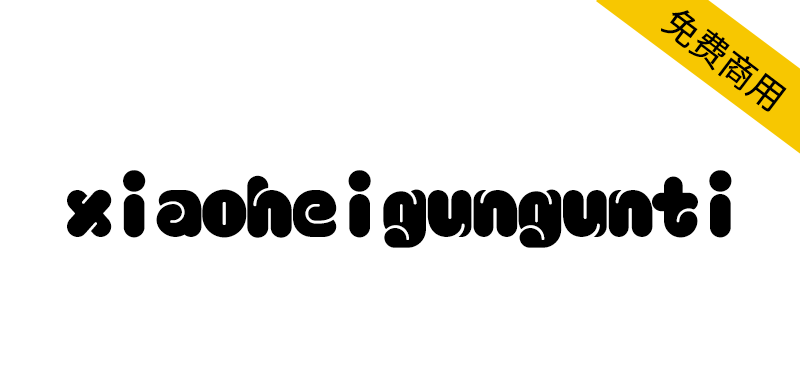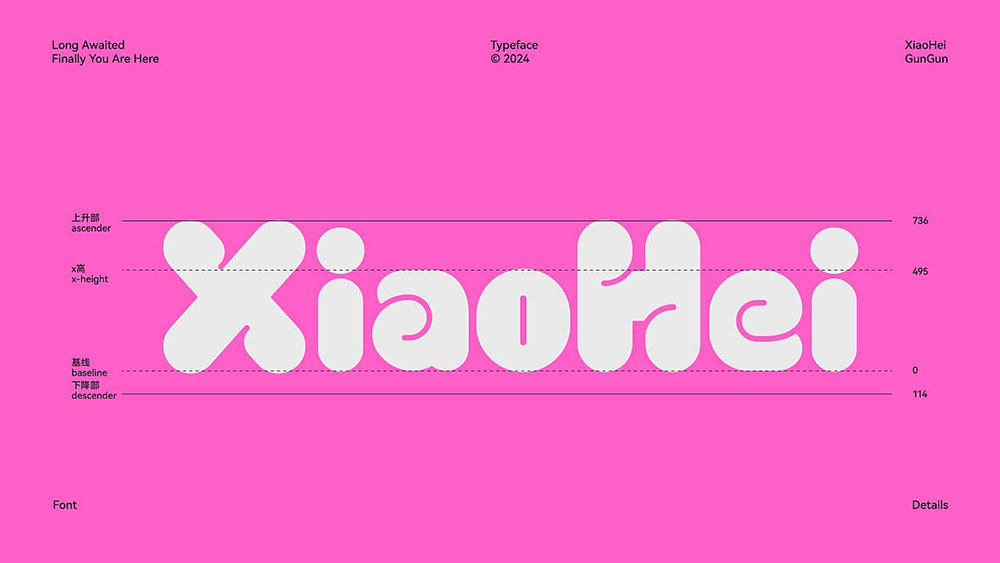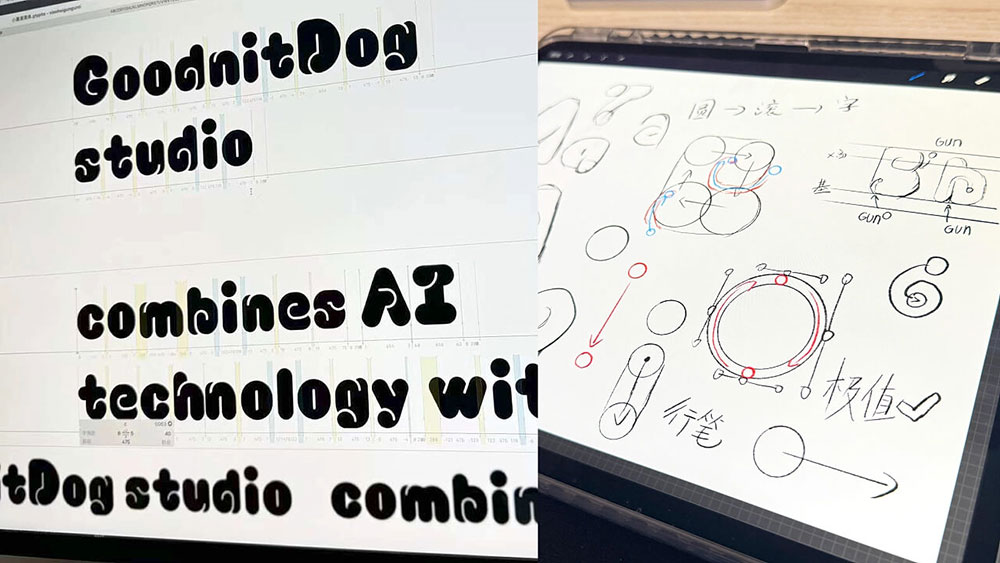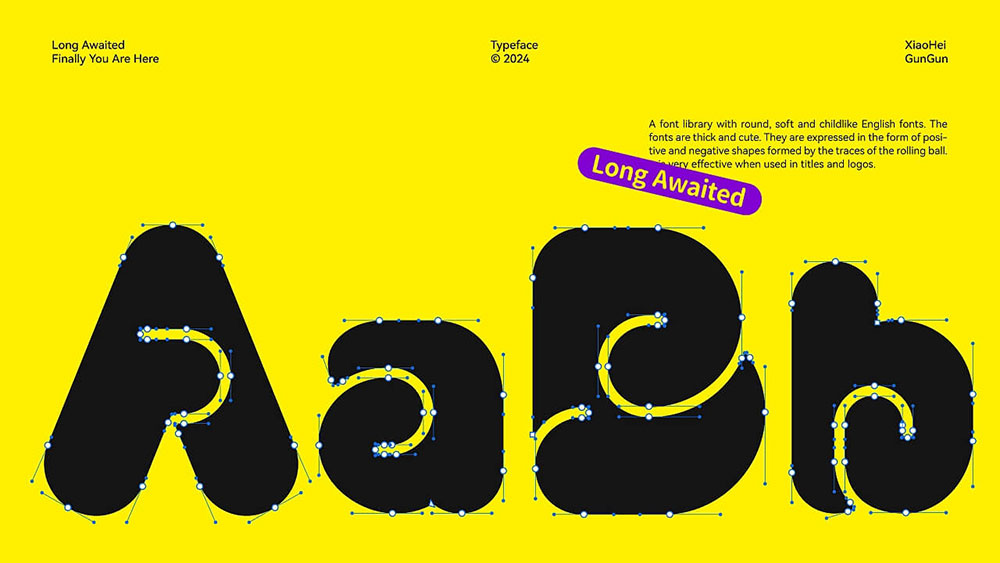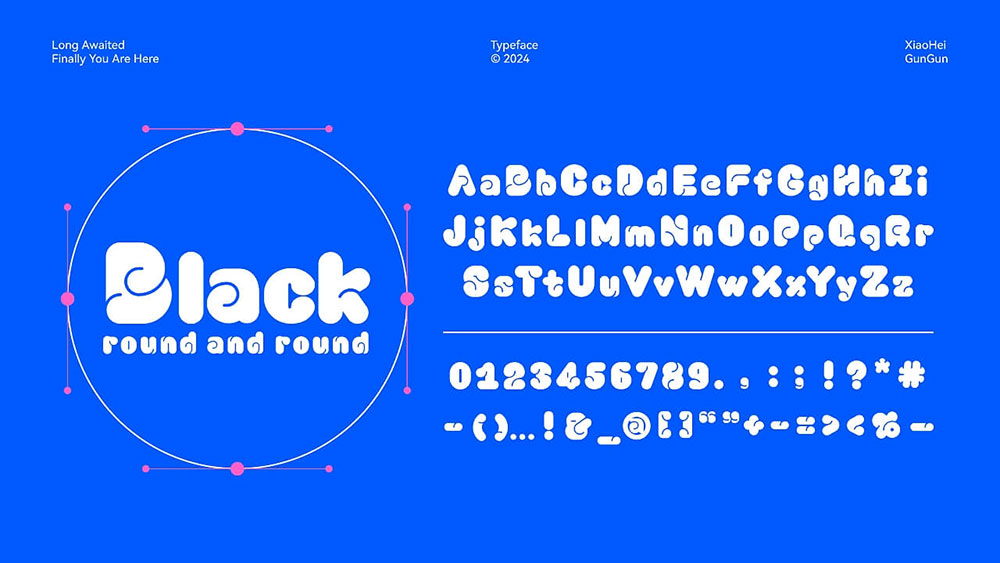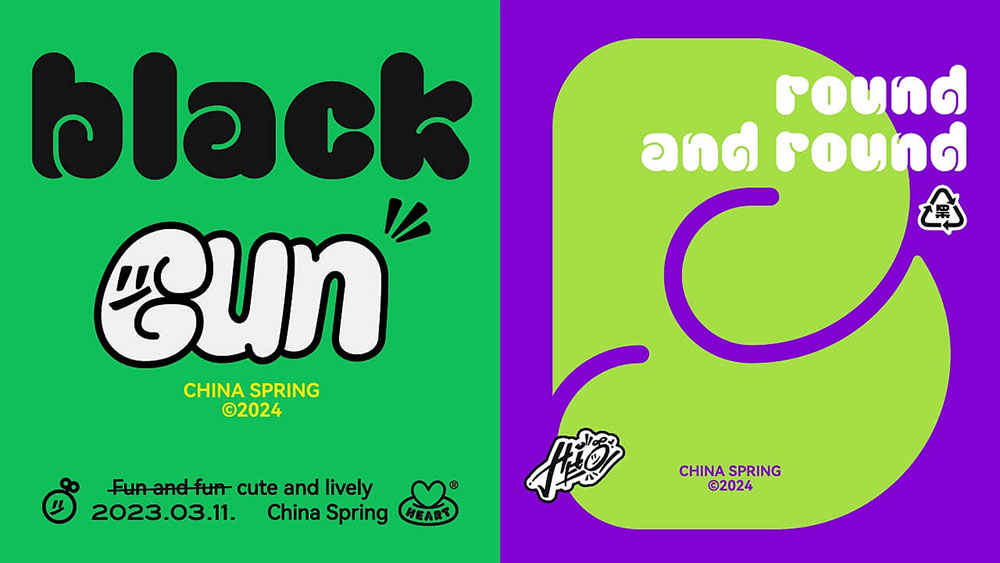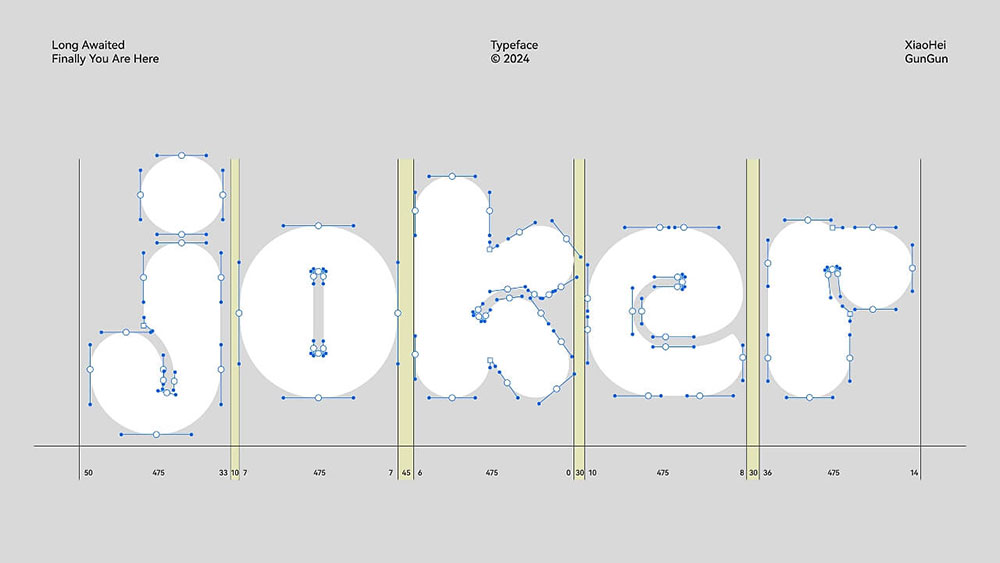
【小黑滚滚体】浑厚可爱,用在标题、logo文字中效果极佳
小黑滚滚体 / 英文字库设计
设计团队丨GoodnitDog studio 观念狗
完成日期丨2024年3月
字体设计丨小黑
动效设计丨入墨 / 北也
秉承自由的理念,浑厚可爱,运用圆滚动后的痕迹形成正负形的形式,根据书写逻辑融合几何图形运动去表达,用在标题、logo文字中效果极佳。